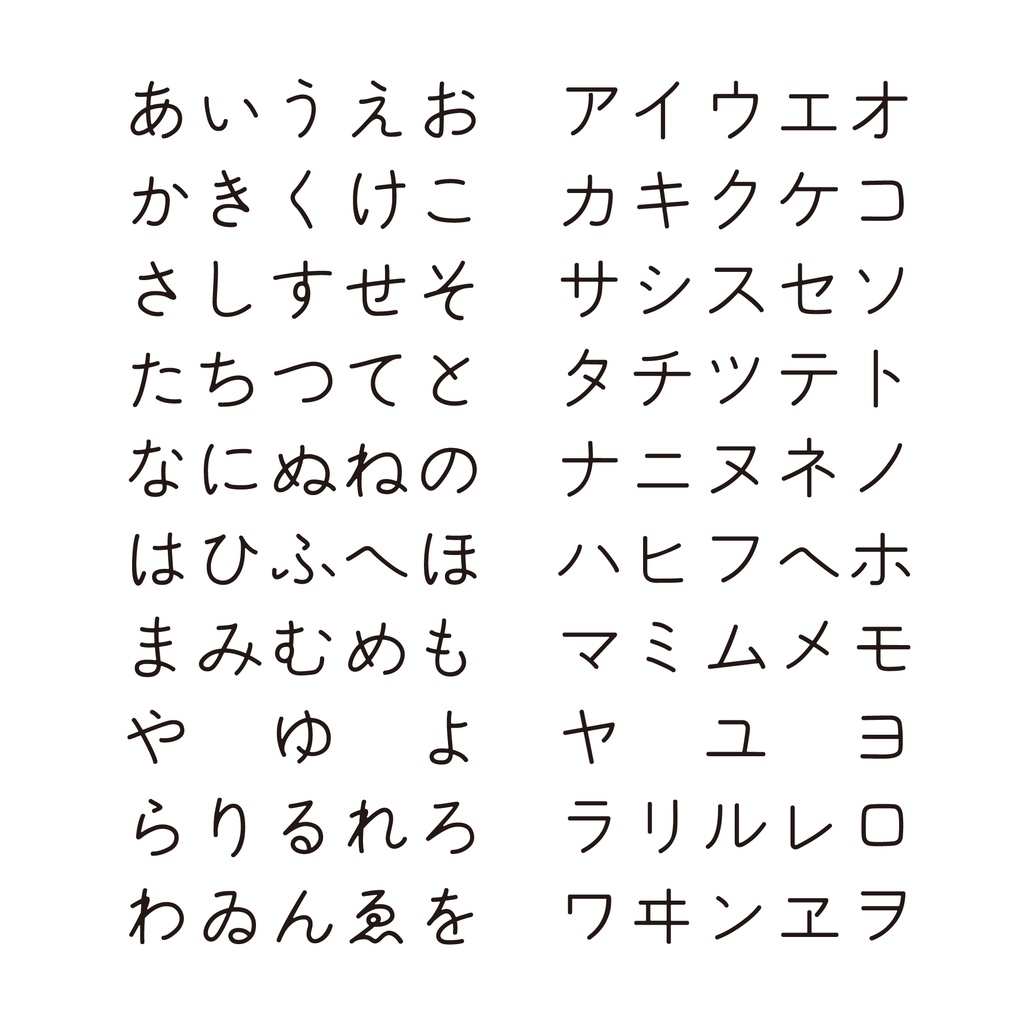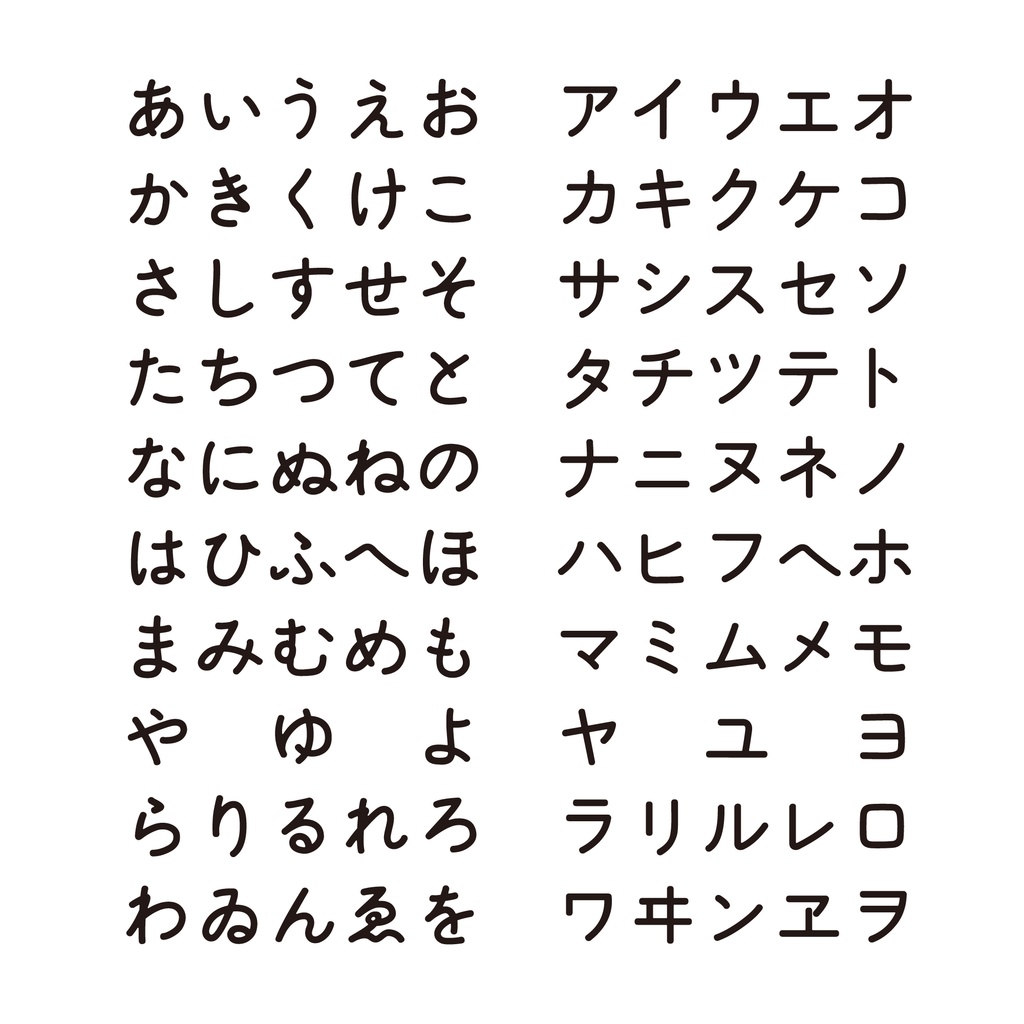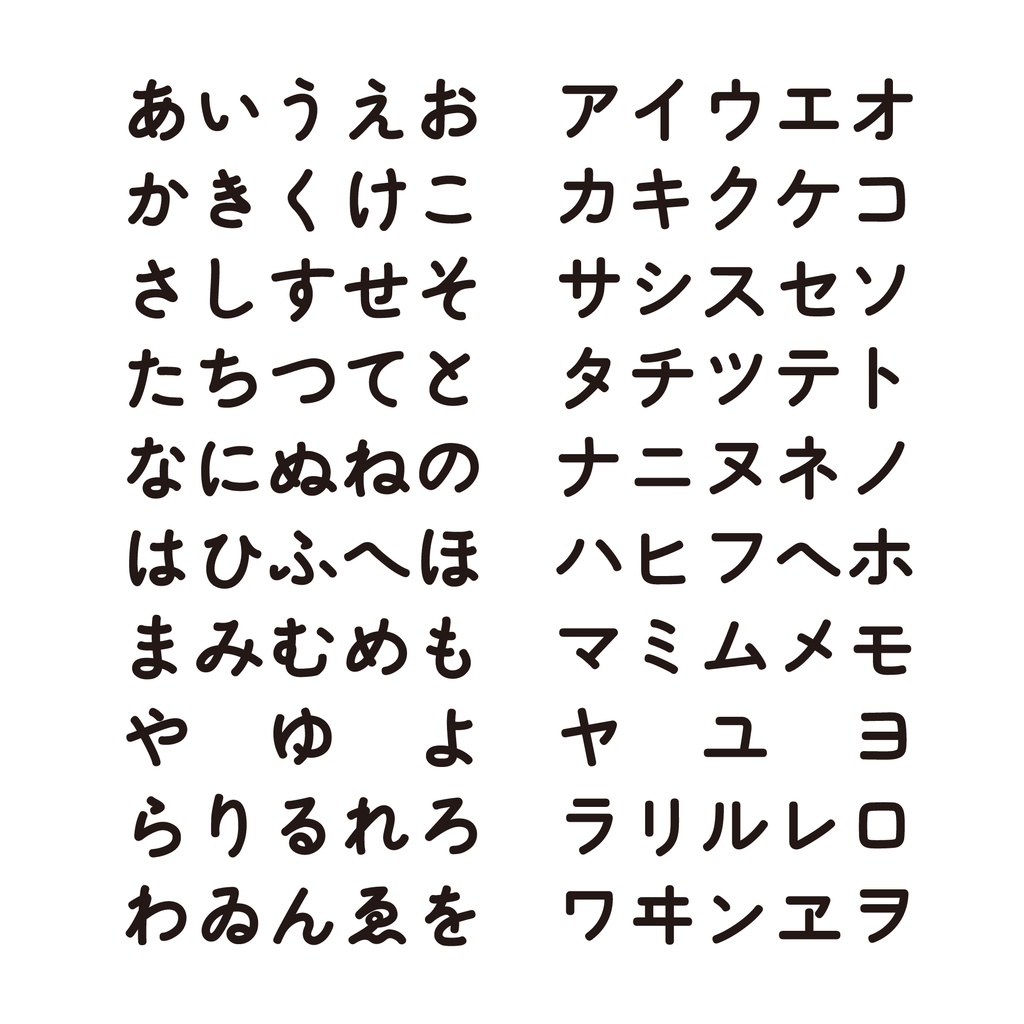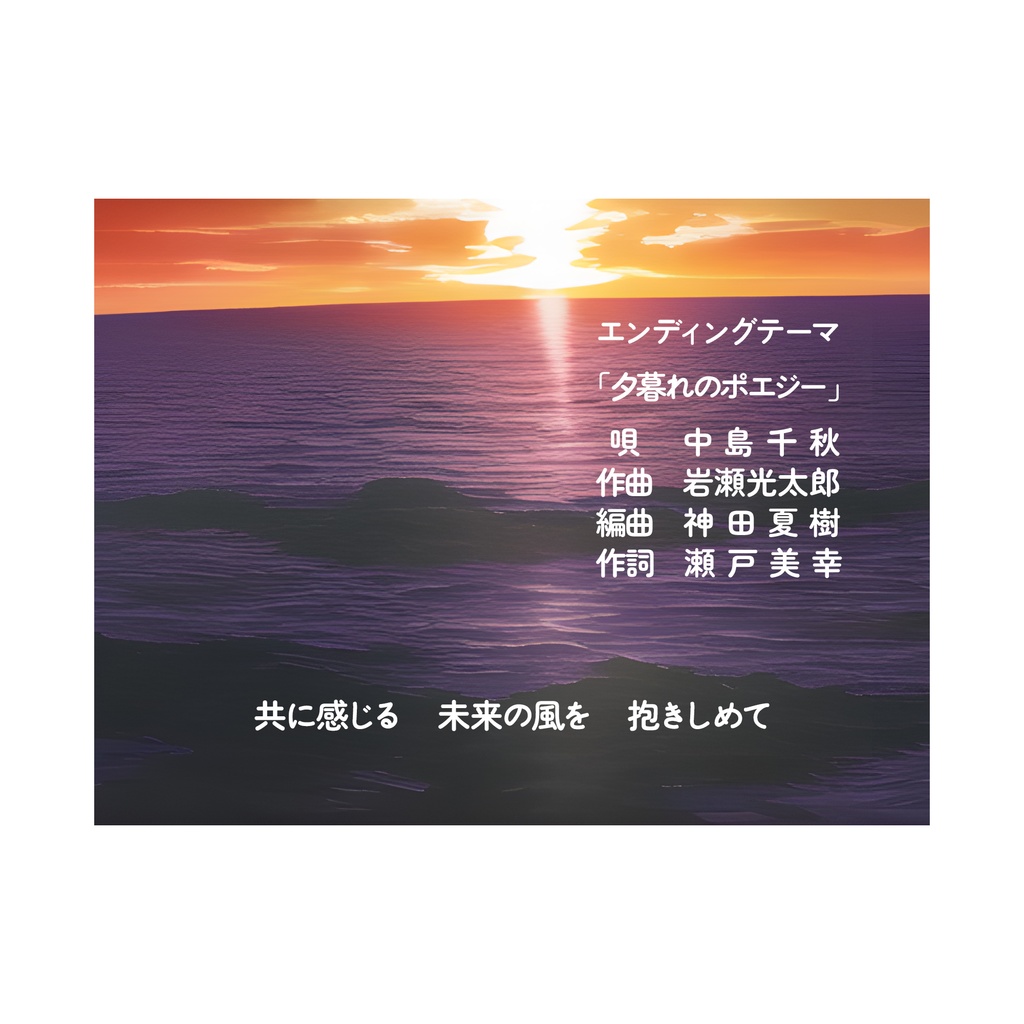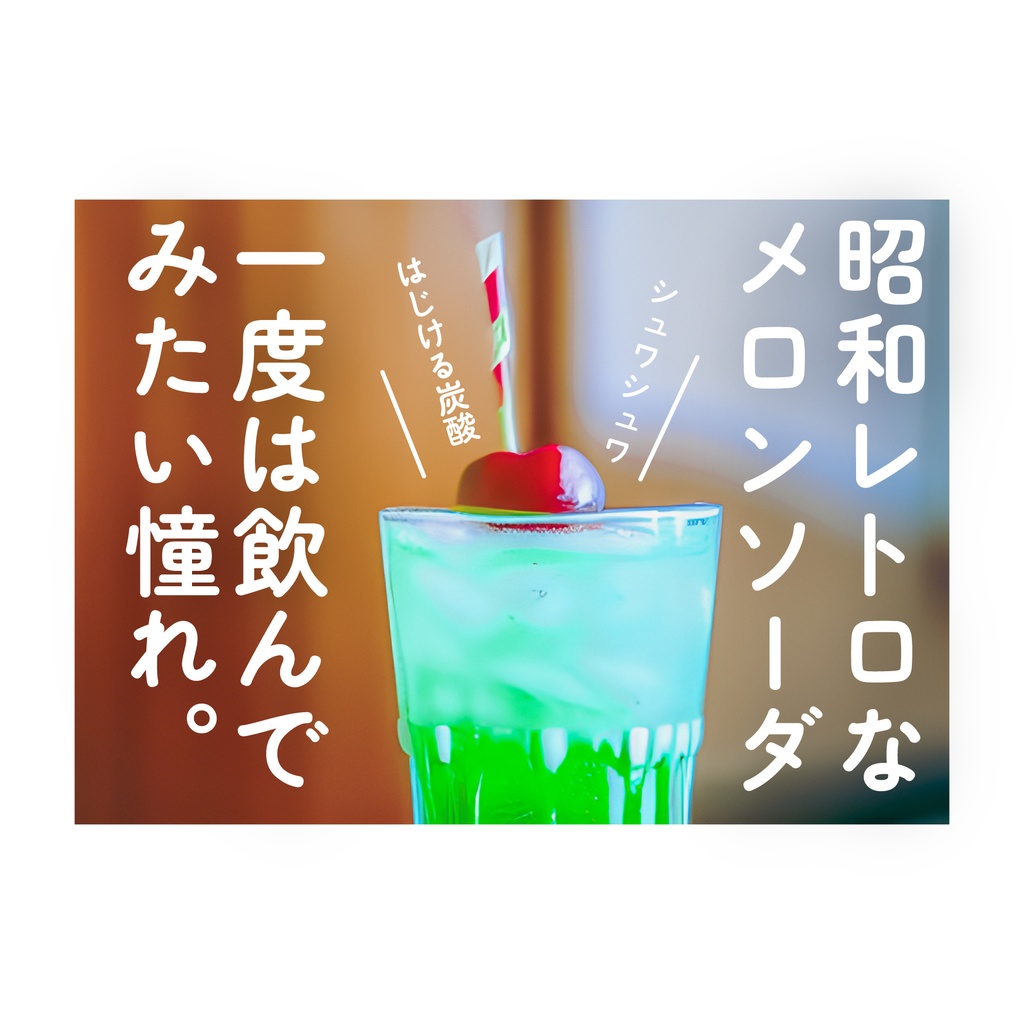
この度は新レトロ丸ゴシックをダウンロードいただき誠にありがとうございます。 ■書体概要 新レトロ丸ゴシックは写植時代に使われていた丸ゴシックを参考に作られました。懐が狭めで表情のある柔らかな仮名は、昭和~平成の印刷物やテレビのテロップ雰囲気を出すのに似合うはずです。特に一画目が突き抜けた「と」のデザインが特徴的です。 ウェイトは使いやすいRegular、Medium、Bold三種類で見出しから本文まで幅広く使用できます。 かなと一部約物を除き「ZEN丸ゴシック」から利用しています。 また、制作にあたり情報の提供をいただきした、書体讃歌(@typeface_anthem)さんとオリジナルのフォントに深く感謝いたします。 ■エディションの違い 「新レトロ丸ゴシック(アドビ製品向け)」を使うとアドビ製品のIlustratorやPhotoshopなどでは1つのフォントとしてウェイトの切り替えができます。 「新レトロ丸ゴシック(上記の~)」を使うと3つのウェイトごとに別々のフォントとして識別されます。Officeなどのソフトで正しく動作しない方向けに用意しています。(当方、Officeの環境がないため持っている方に試してもらっています。) ■ご利用にあたり SILオープンフォントライセンスでの配布なので、商用・個人利用可能です。 2023/03/11 Ver1.000 公開 2023/03/13 Ver1.001 Wordなどで一部のウエイトが使用できない問題を修正 2023/03/14 Ver1.002 縦書き時の不具合修正 2024/03/11 Ver1.003 ウェイトが正しく選べない問題を修正。アドビ製品向けとOfiiceなどその他ソフト向けにファイルを分けました。 Copyright (c) 2024 Typographish All Rights Reserved.